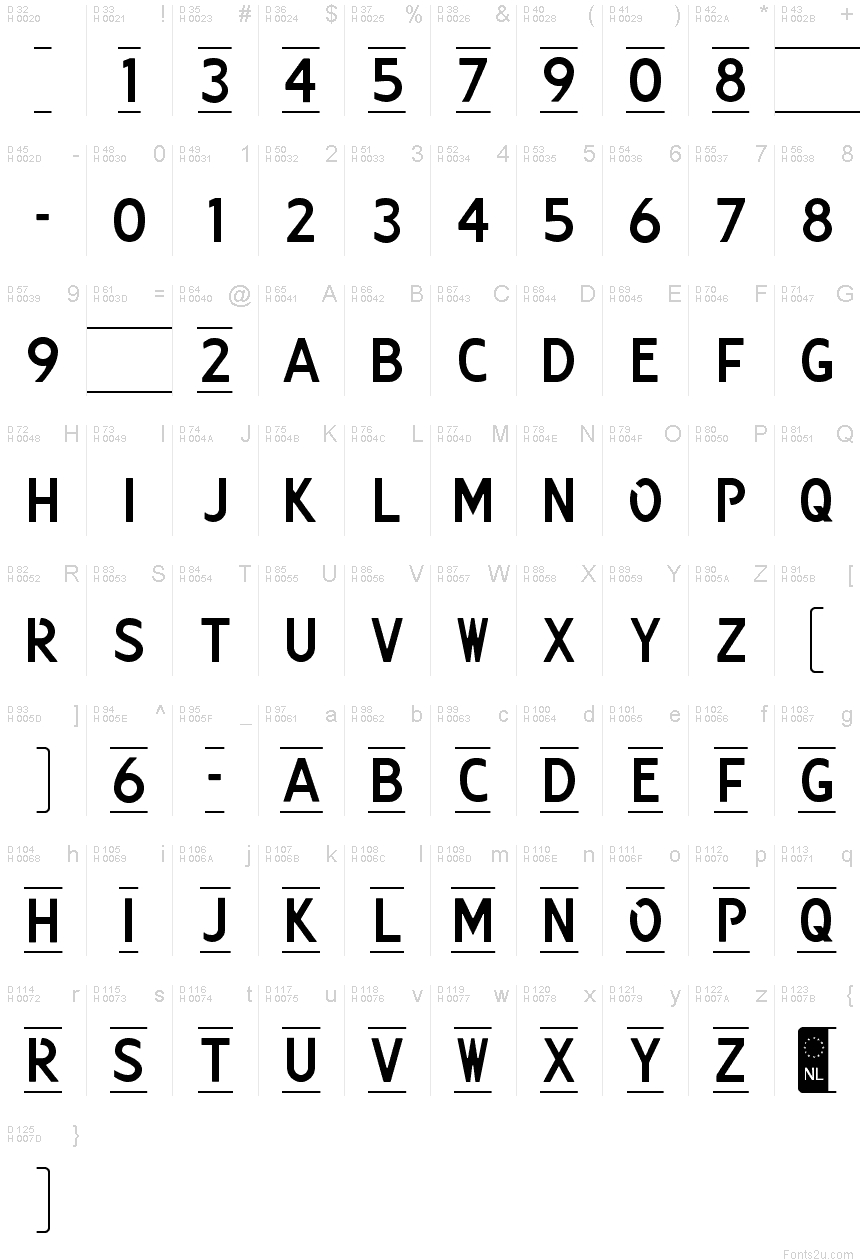
خط Kenteken من تصميم Lefly هو خط عرض (display) مجاني بلمسة زخرفية، يحمل في طياته الطابع الصناعي القوي المألوف في أرقام لوحات السيارات. حروفه المرتفعة ذات الجوانب المستقيمة، ووزن الخط المتساوي، ونهايته الأفقية الحادة، تمنح النص شعورًا صلبًا وكأنه مطبوع على المعدن، كما لو كان مدموغًا في الفولاذ أو المينا. يتمتع الخط بإيقاع متقن ومحكم، مما يجعل حتى الكلمات القصيرة تبرز بقوة كأنها لافتات مرورية بدلاً من مجرد خط مطبعي رقيق.
استخدم Kenteken لإضفاء طابع صناعي وتصميم مستوحى من الطرق على الملصقات، ورسومات المركبات، وأرقام السباقات، وهوية الفعاليات، والعناوين التحريرية، وأنظمة التوجيه. يبرز هذا الخط المجاني بشكل خاص عند استخدامه بالأحرف الكبيرة ومع ترك مساحة أفقية كافية له؛ وللحفاظ على مظهر حاد وعملي، ادمجه مع خط (sans serif) هندسي بسيط للنصوص الأساسية.